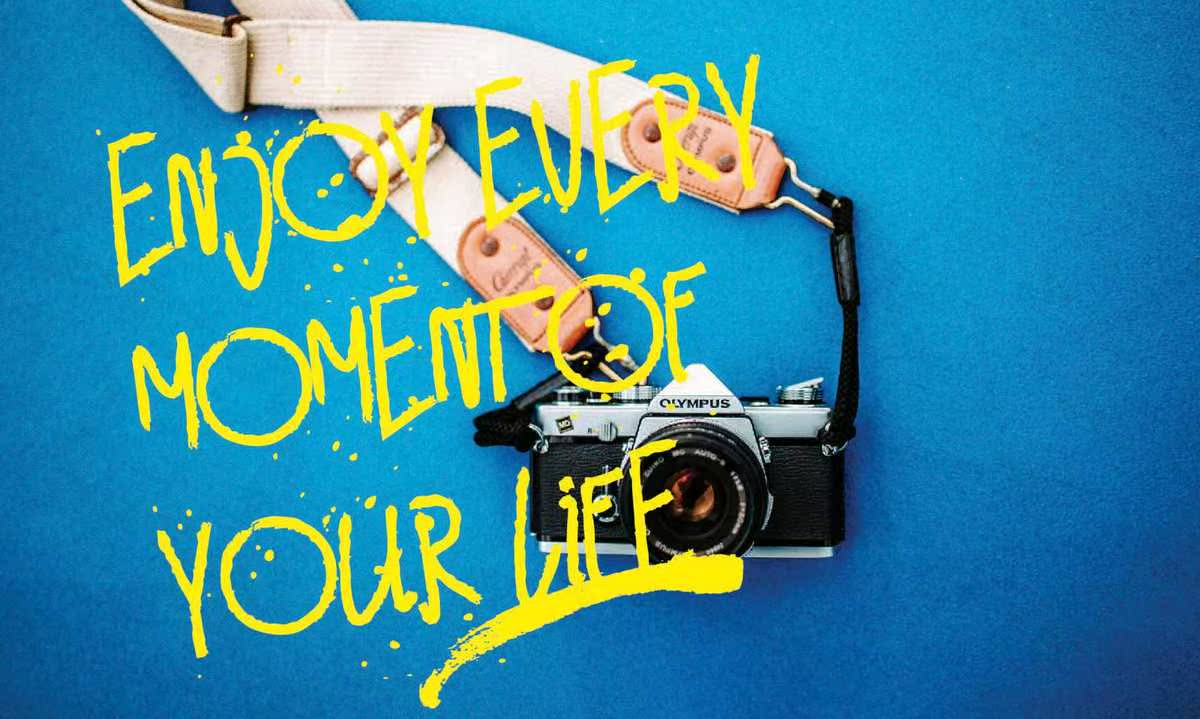
介绍BernakFont,Astyleof和Writing with a DistinctiveStyle。这款美丽的画笔可以让您通过Legent、Classic和ModernLook亲自接触到您的最新项目。介绍BernakFont,Astyleof和Writing with a DistinctiveStyle。这款美丽的画笔可以让您通过Legent、Classic和ModernLook亲自接触到您的最新项目。